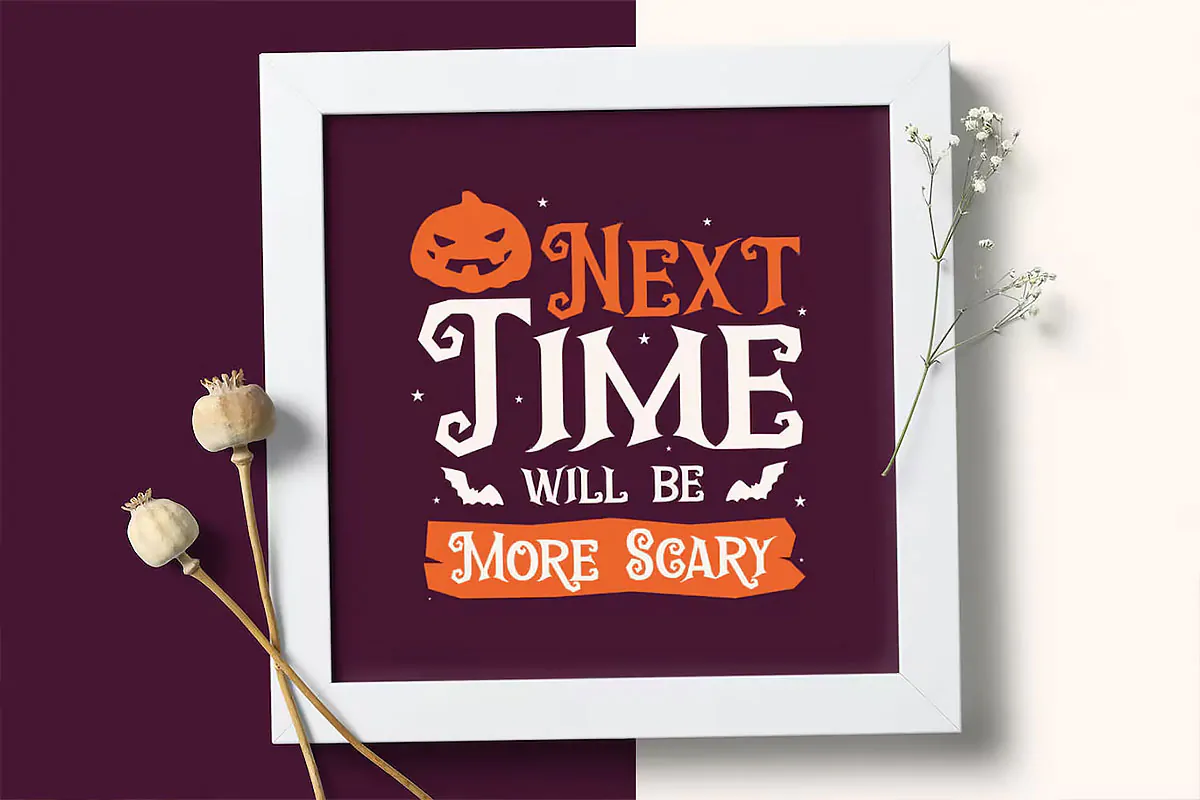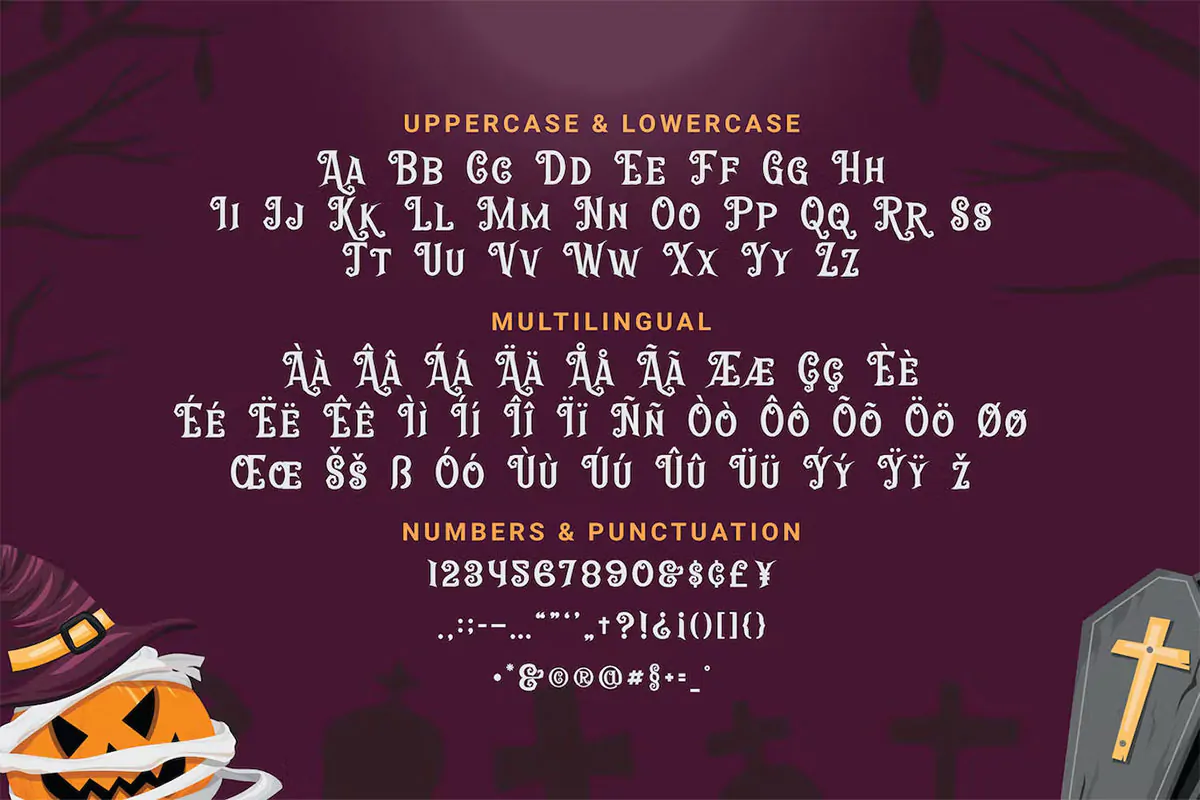
فونت هالووین Antique
فونت هالووین انگلیسی
فونت هالووین Antique یک قلم نمایشی انگلیسی فوق العاده زیبا است که مناسب برای استفاده در طرحهای گرافیکی مختلف به خصوص طراحی انواع پوستر ویژه هالووین میباشد.